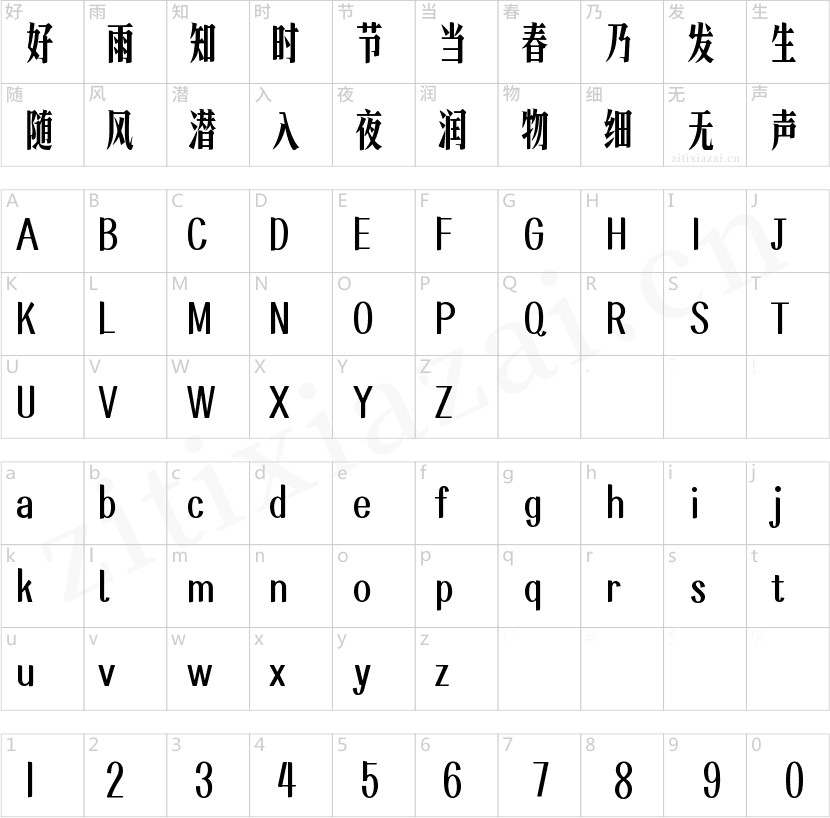
也字工厂港风宋体
也字工厂港风宋体,这款字体结构工整、笔画清晰,兼顾美观与易读性,适用于标题、正文、海报、包装、LOGO 等多种场景。字形优雅稳定,风格百搭耐看,适配日常排版与创意设计,让文字呈现更舒适、更具质感。也字工厂港风宋体一笔一画,皆是细节,以均衡的比例、流畅的线条打造舒适视觉体验,字形端正大气,风格简约现代。无论是商业设计、品牌宣传还是日常排版,都能轻松驾驭,让文字更有格调与力量。也字工厂港风宋体字体下载。